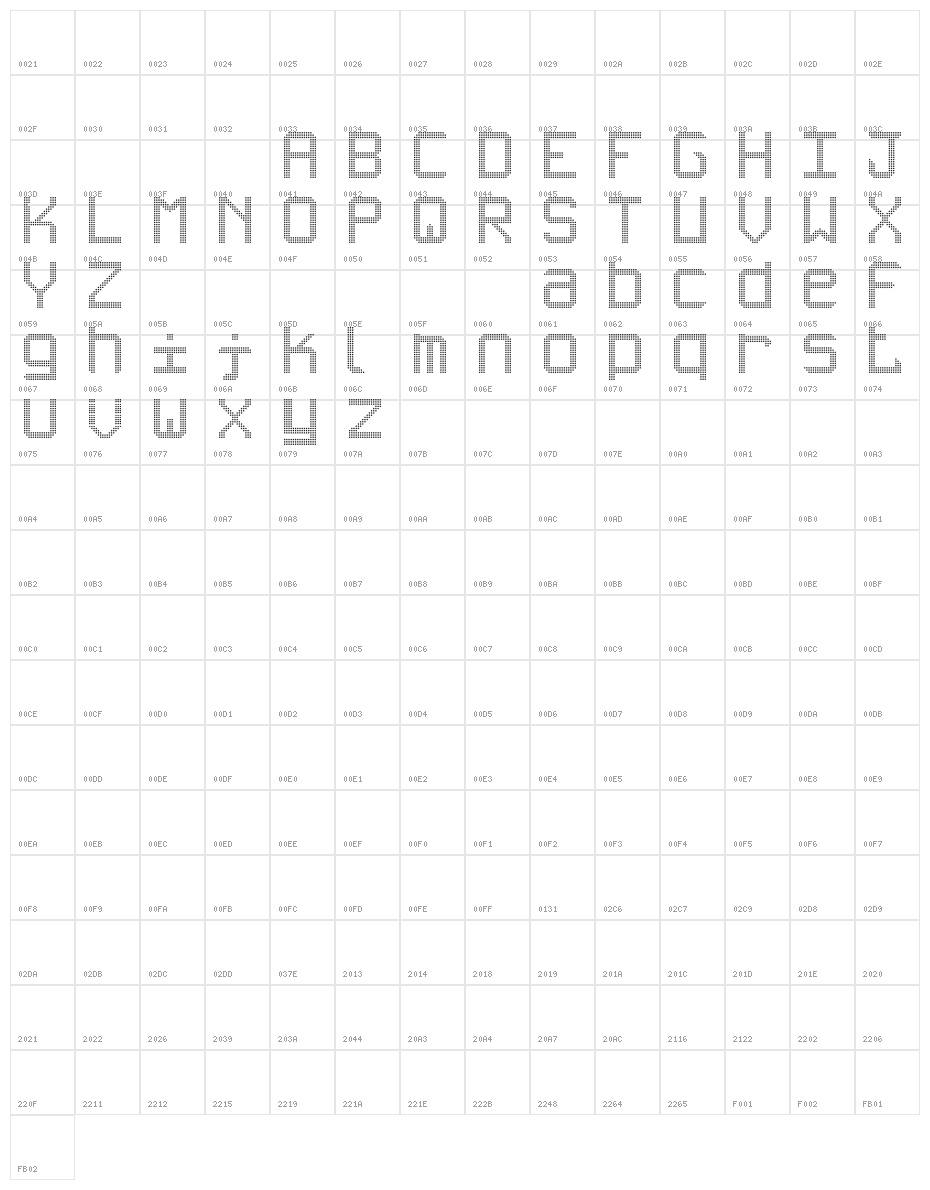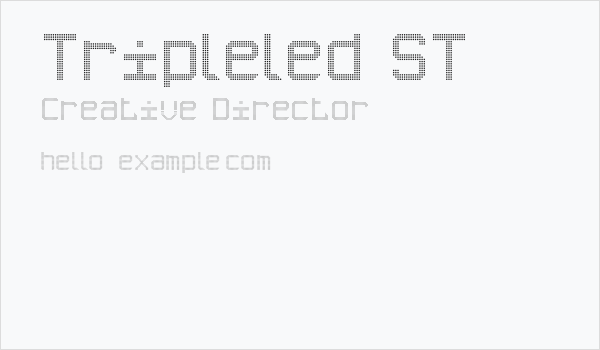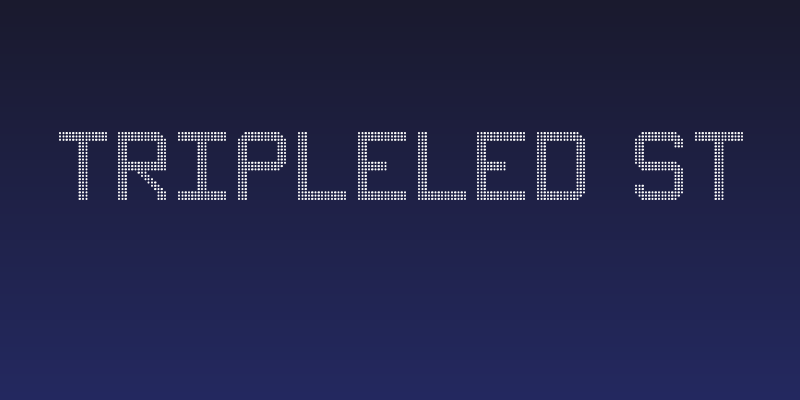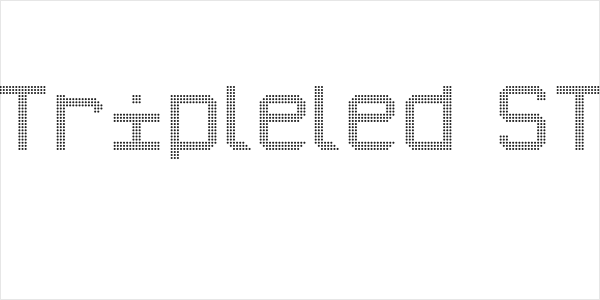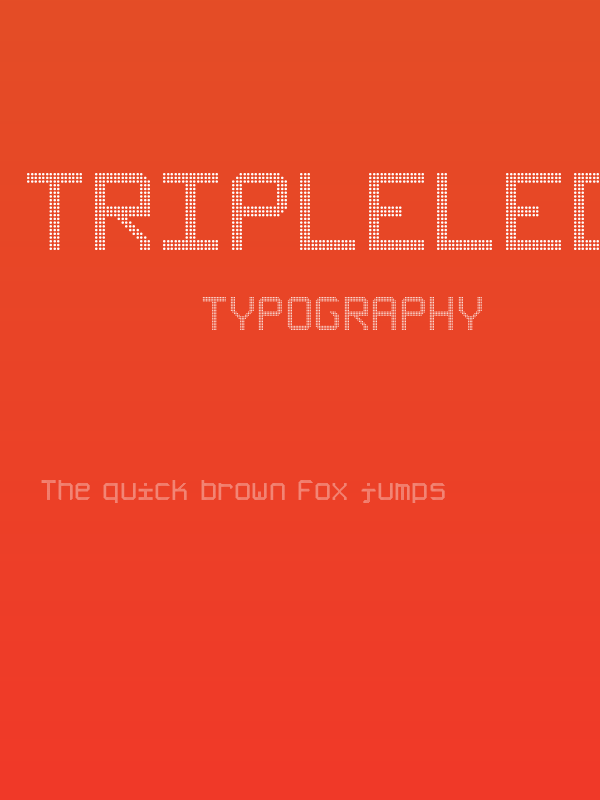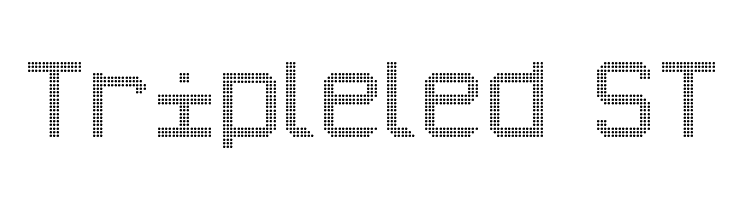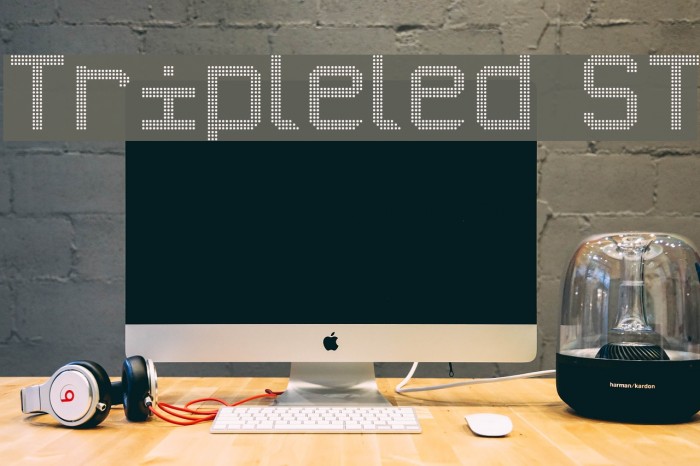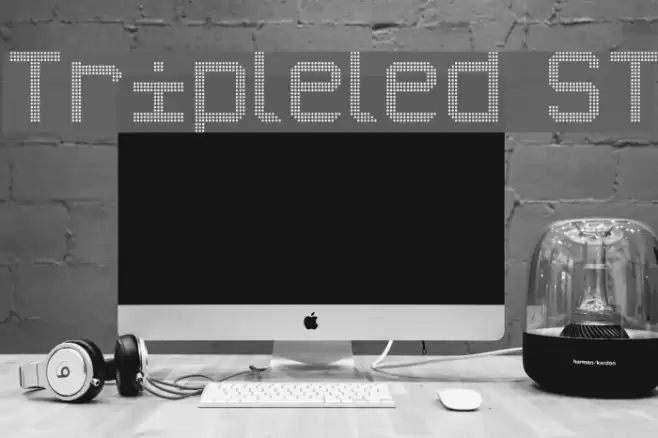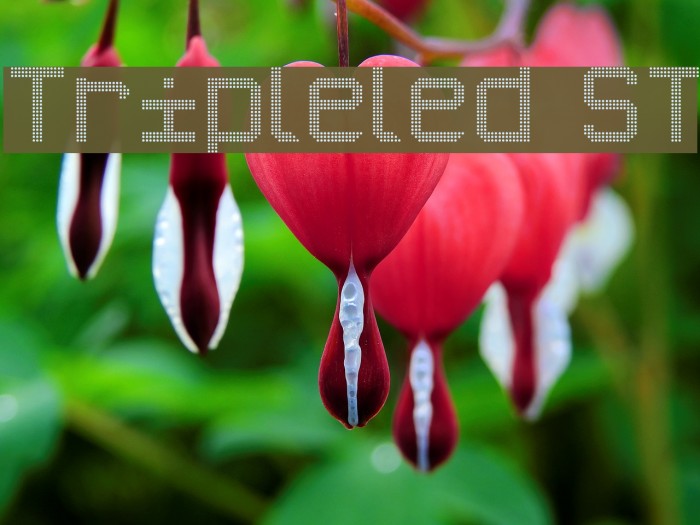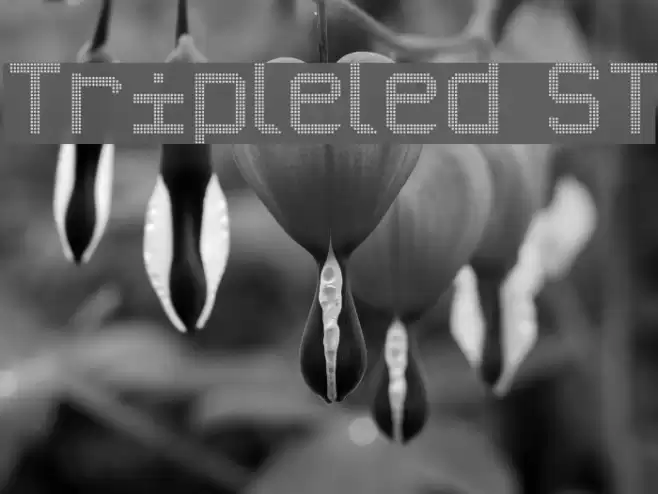
Tripleled ST Font
| Style général | Retro, Digital |
| Projets proposés | Ideal for retro-themed designs, digital art projects, tech-related branding, and nostalgic print materials. |